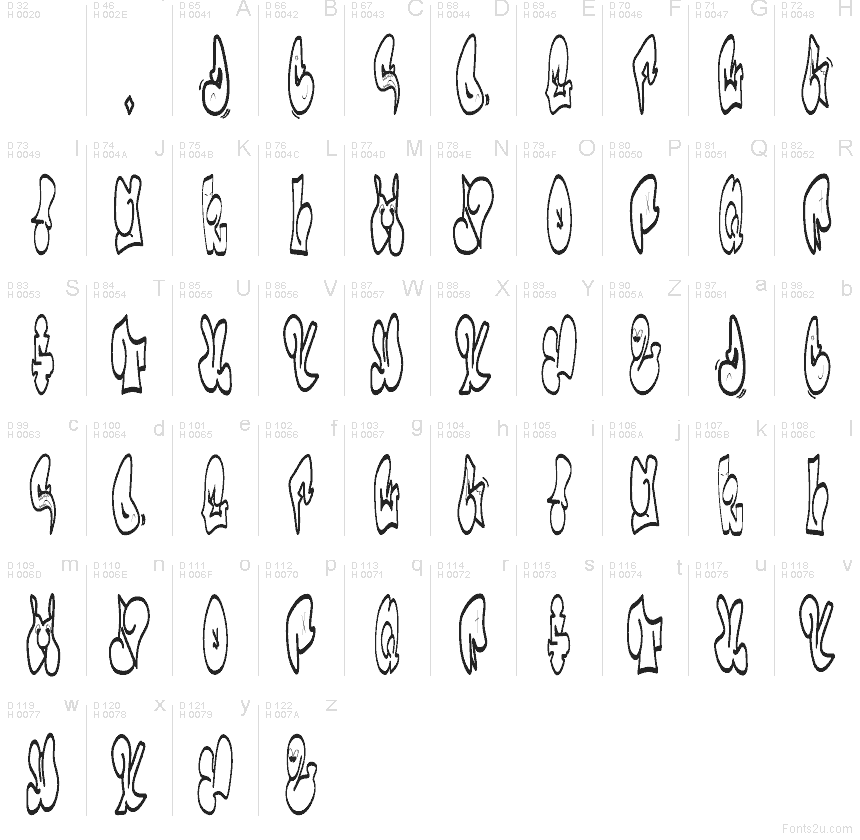
Ugly Faces
Ugly Faces — это бесплатный шрифт в стиле граффити, передающий свободный дух уличного теггинга. Буквы отличаются длинными, пружинистыми штрихами и раздутыми, «пузырчатыми» изгибами, а неровная высота знаков и резкие завершения придают всему начертанию сырой, дерзкий и динамичный вид.
Шрифт отлично подходит для заголовков на постерах, обложек микстейпов, скейт-графики, шапок зинов и клубных флаеров — везде, где требуется бесплатный шрифт с той самой энергией маркера на стене. Используйте его в коротких заголовках или логотипах: растянутые формы и быстрый ритм уличного тега лучше всего работают в лаконичных надписях.